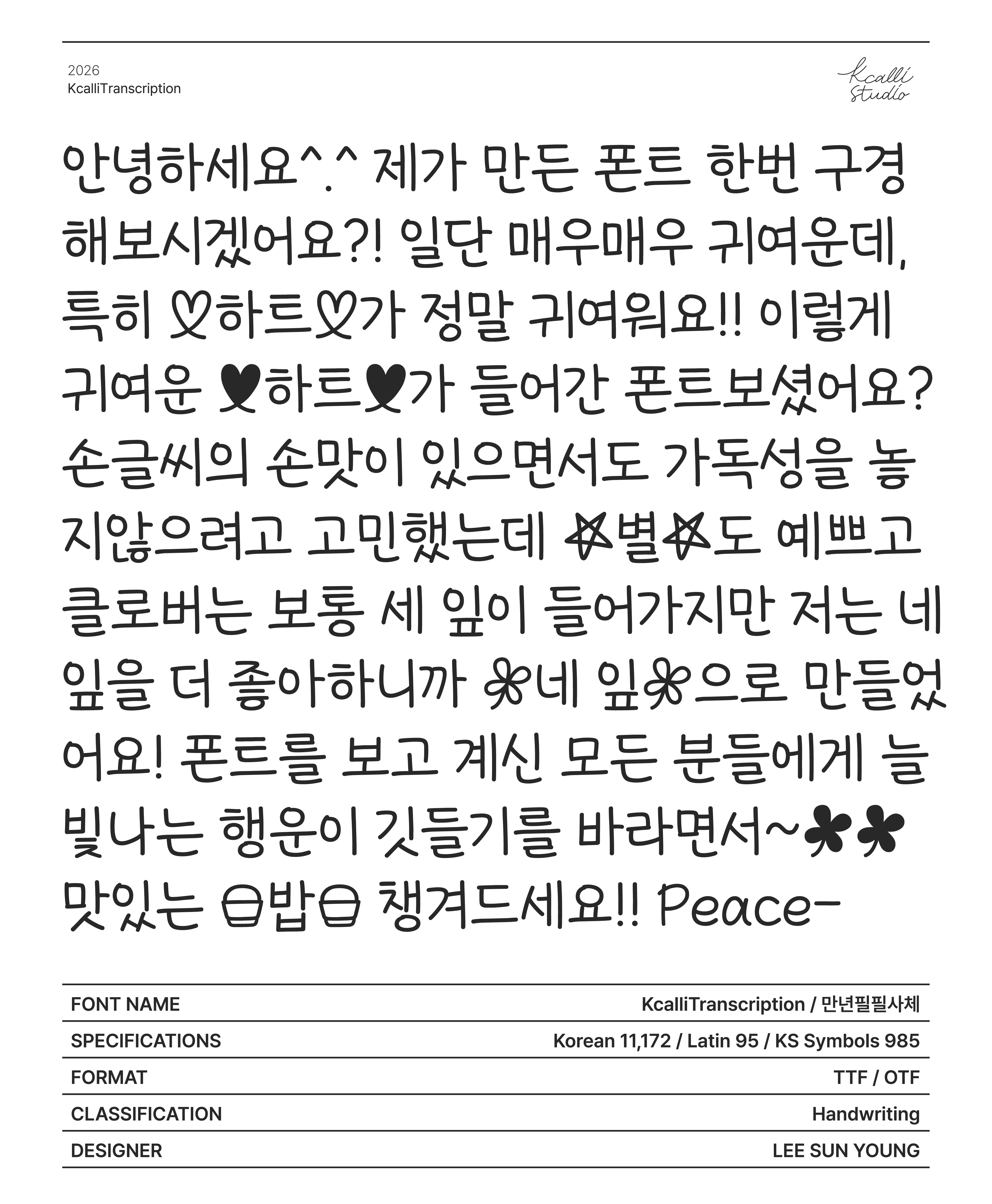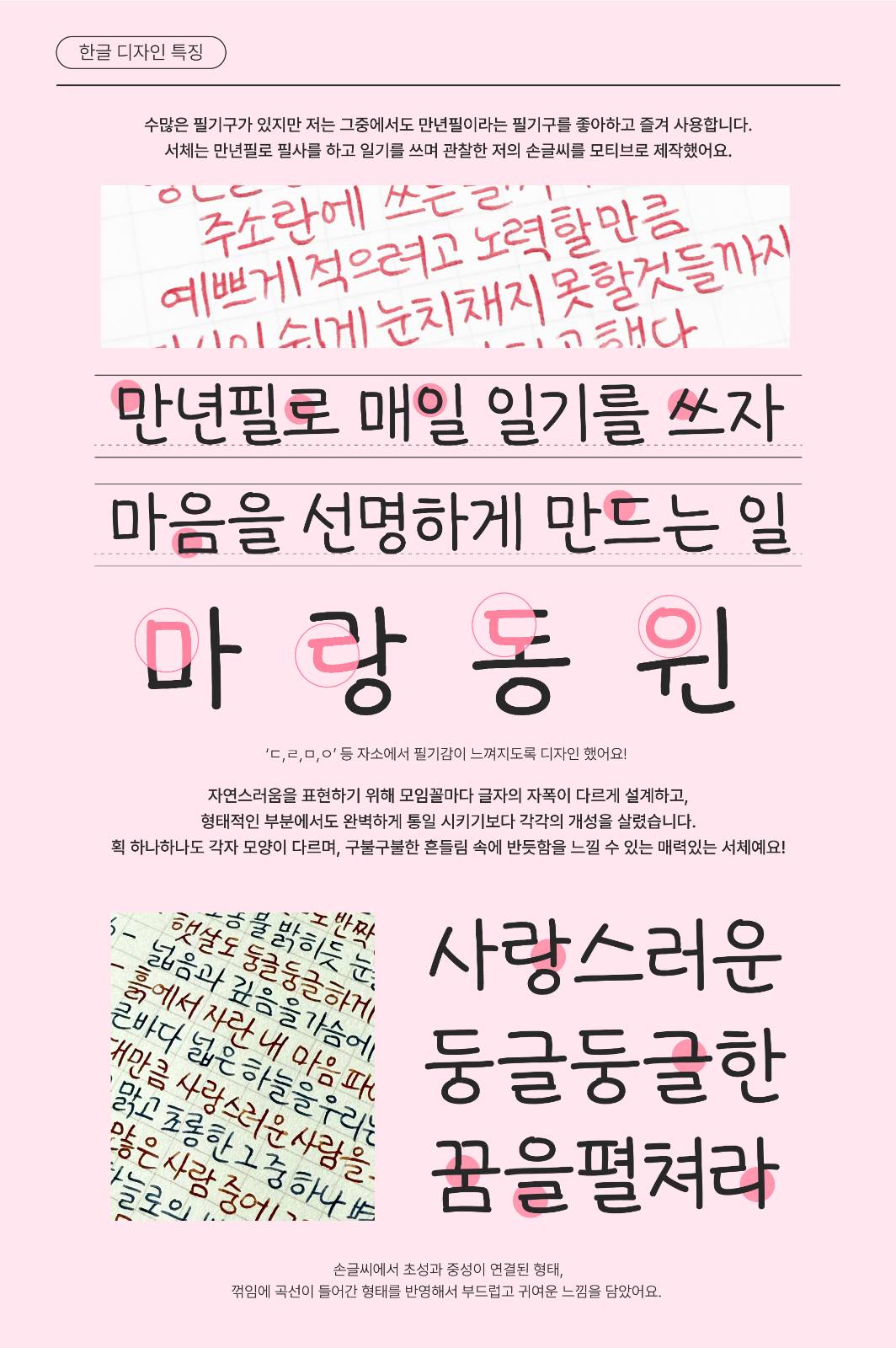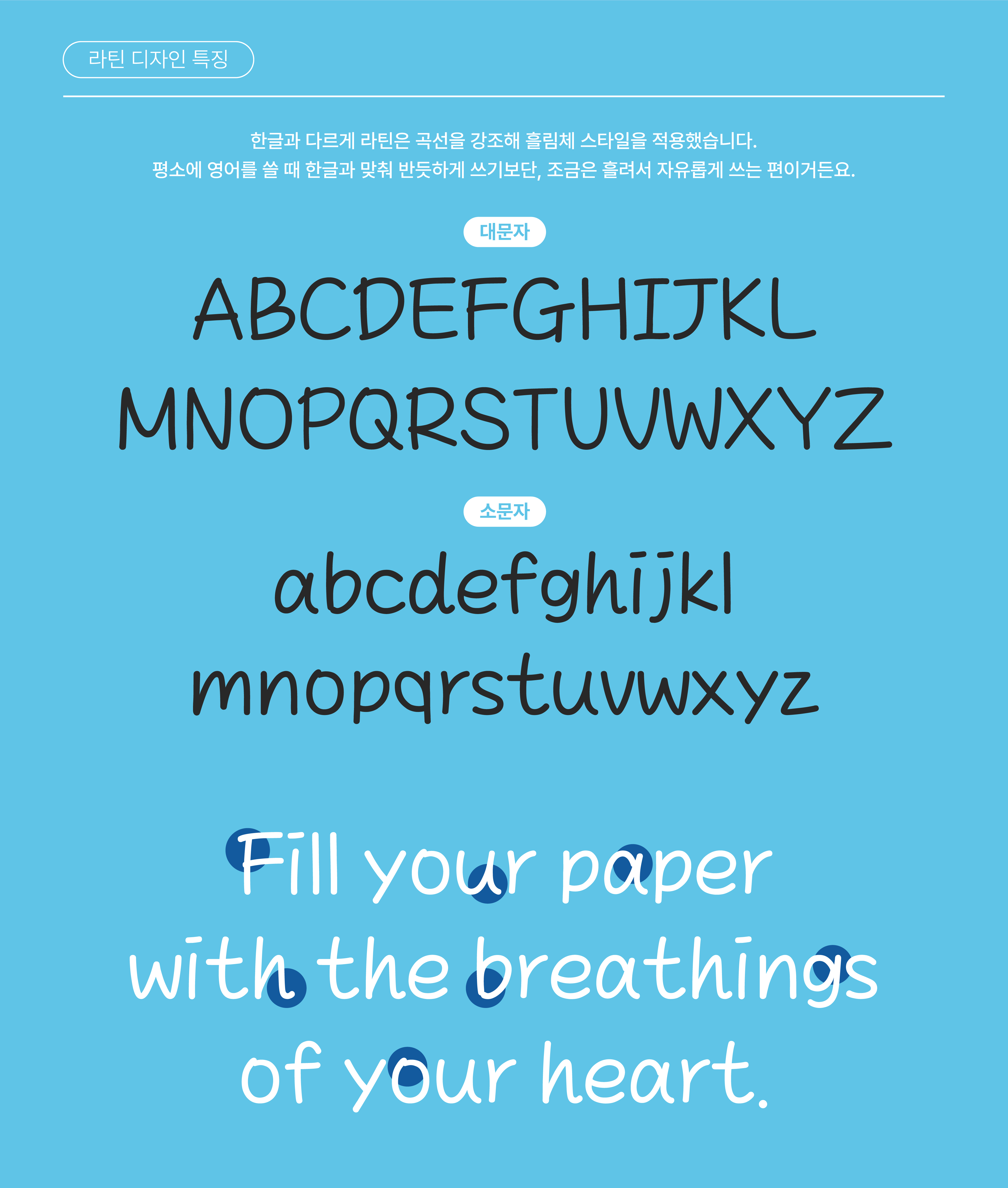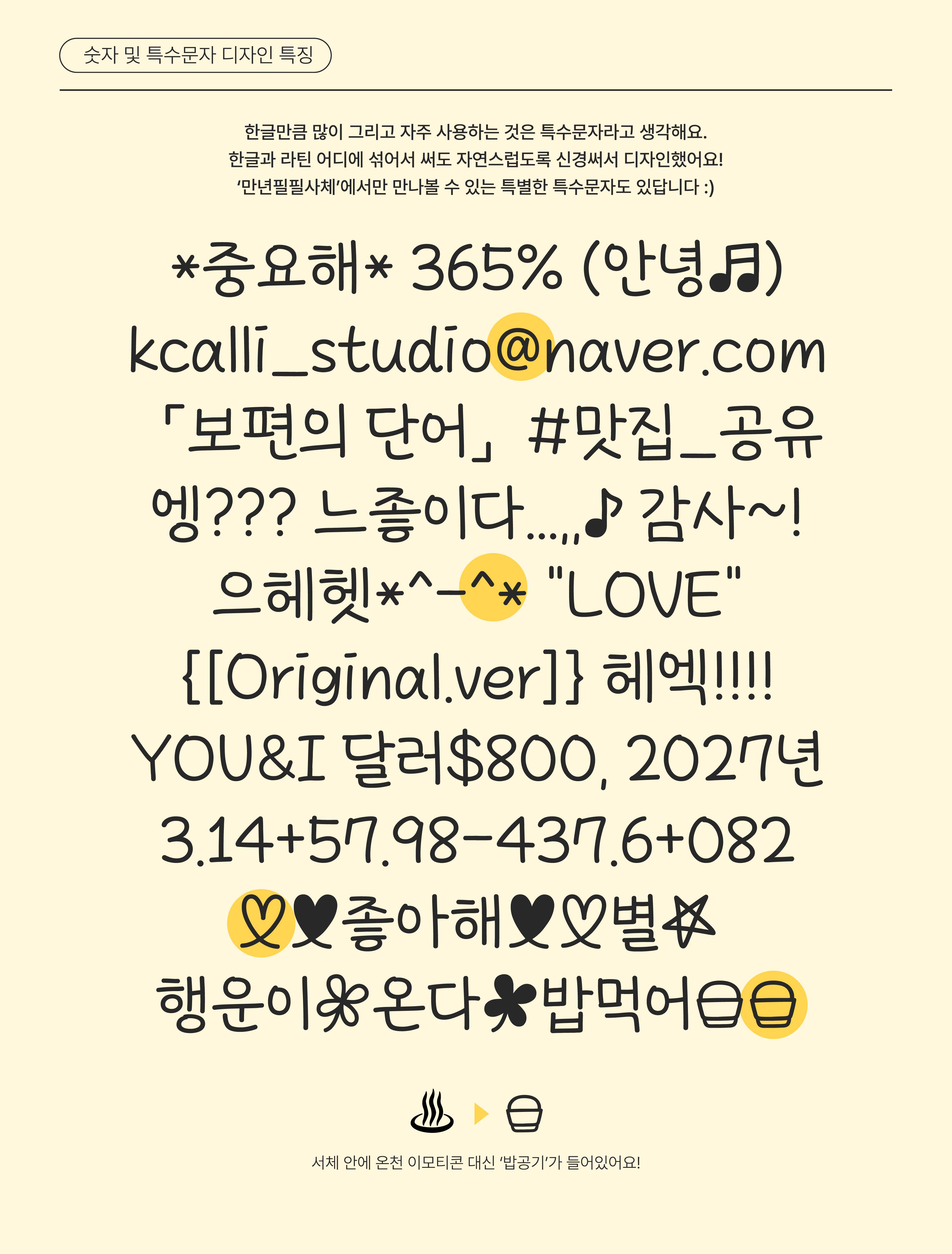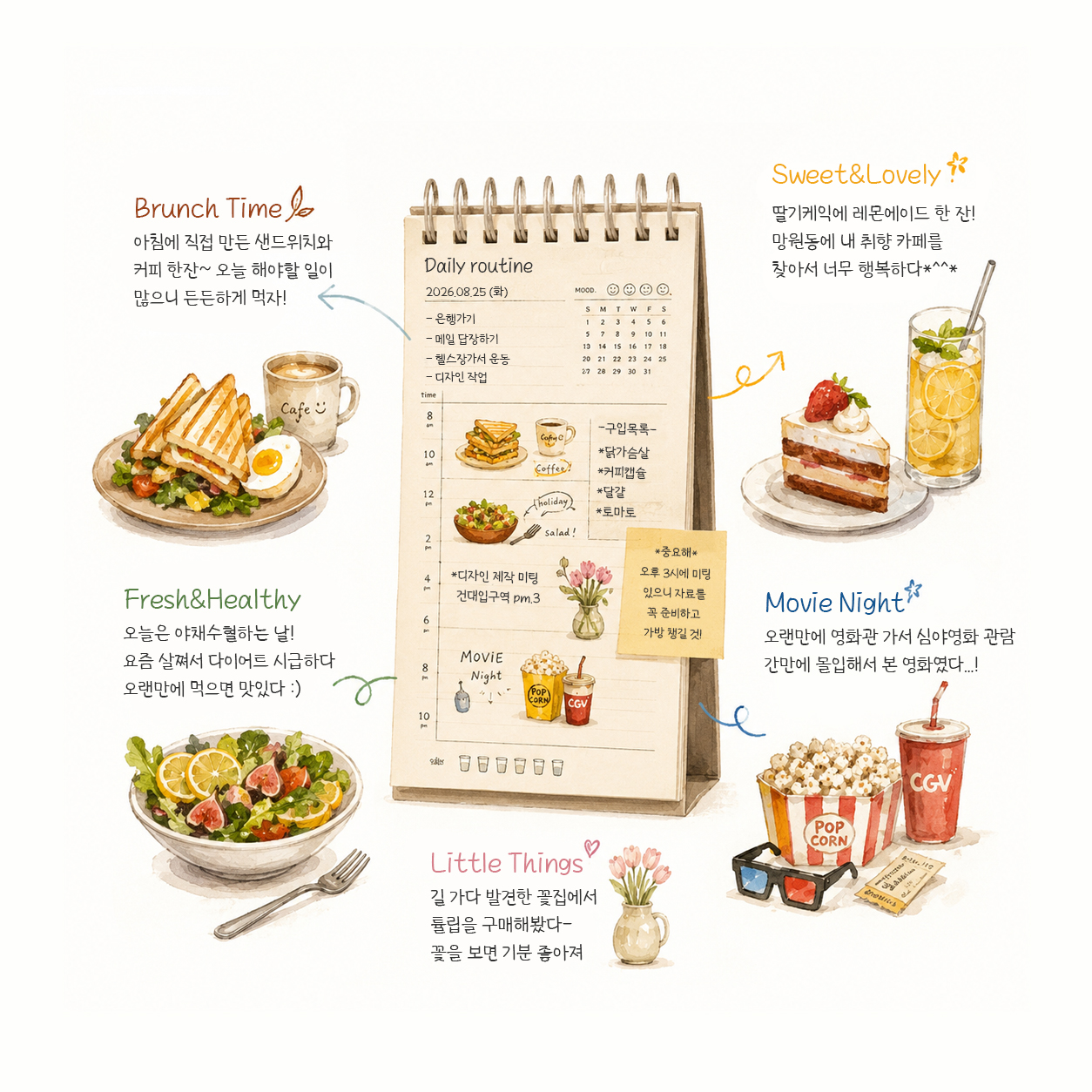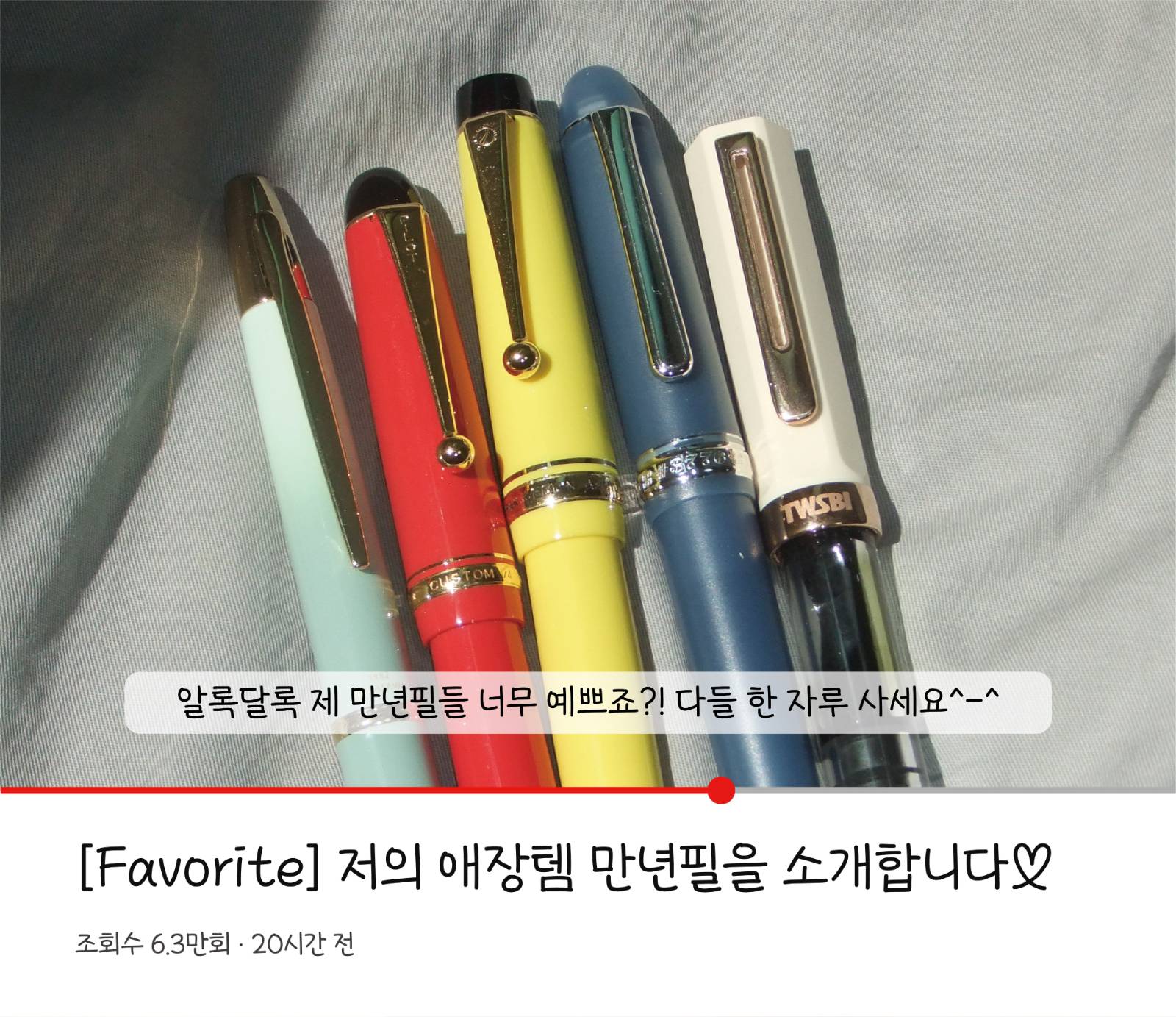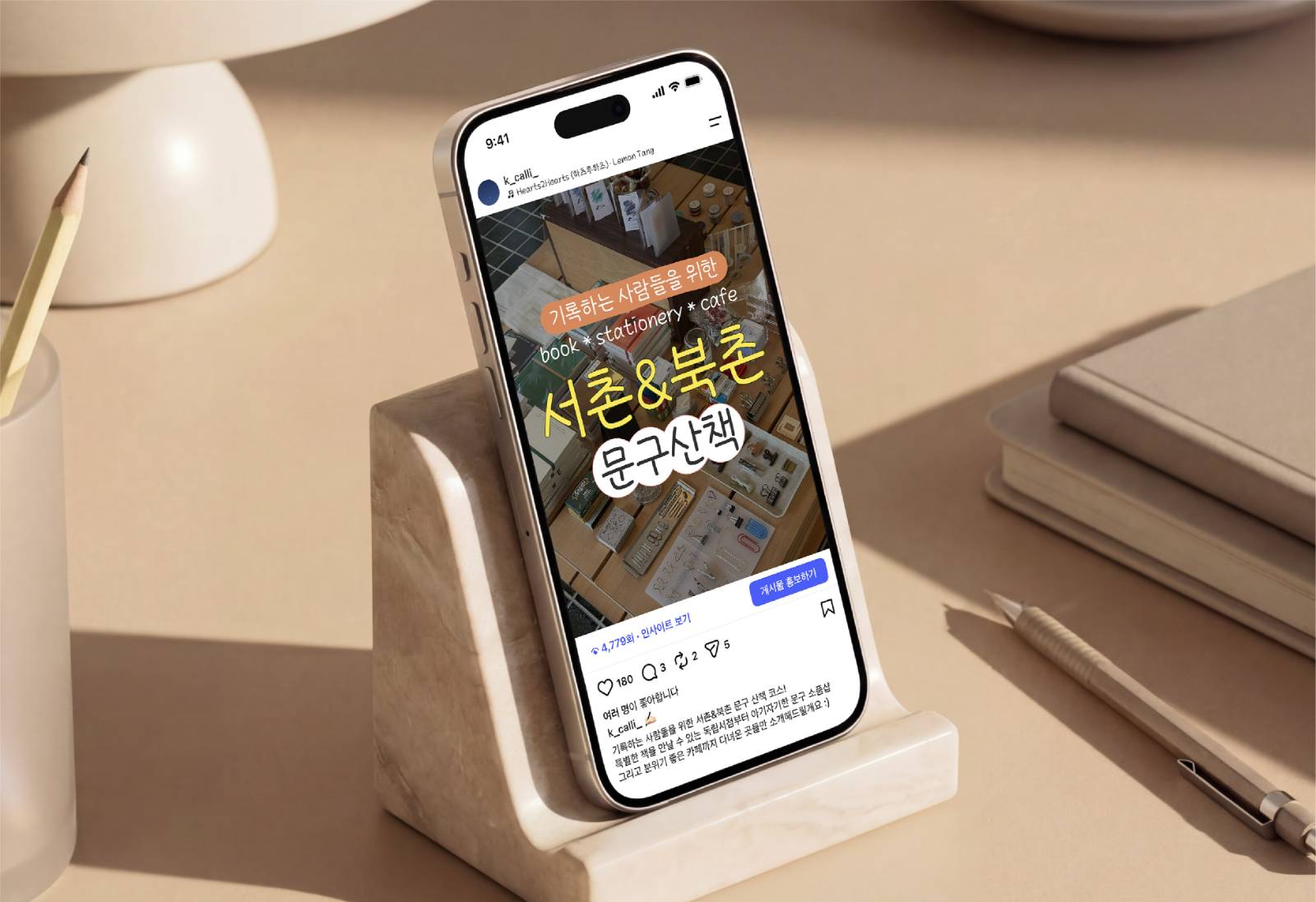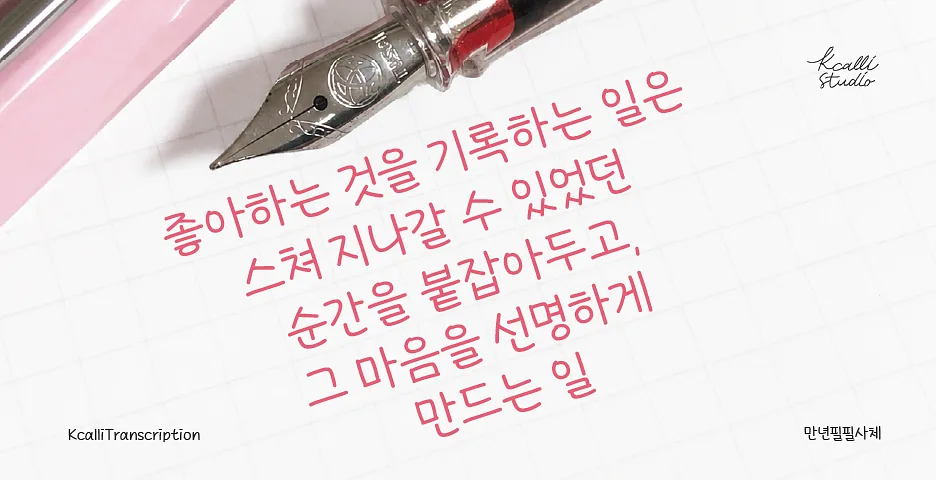
Kcalli만년필필사체
우리가 흔히 손글씨를 매우 잘 쓰는 사람에게 ‘폰트같다’고 칭찬하곤 합니다.
저는 잘 쓴 글씨를 보면 폰트로 쓰고싶은 마음이 담겼다는 점에서 굉장히 독특한 칭찬이라고 생각했어요! 여기서 사람들의 귀여운 모순은 정작 진짜 폰트를 고를 때는 직접 쓴 손글씨의 자연스러움이 묻어나는걸 좋아한다는 거예요. 그렇다면 상반된 두 가지의 니즈를 충족시킬 수 있는 하나의 손글씨 서체는 없을까? 라는 질문에서 이 서체는 시작되었습니다.
정답은 늘 가까이에!
정돈이 덜 된 저의 손글씨엔 상반된 매력이 담긴 특별함이 있다는 것을 발견했습니다. ‘만년필필사체’는 저의 만년필 손글씨를 바탕으로 저만의 스타일을 더해 자연스러운 손글씨의 매력을 새롭게 해석한 서체입니다.